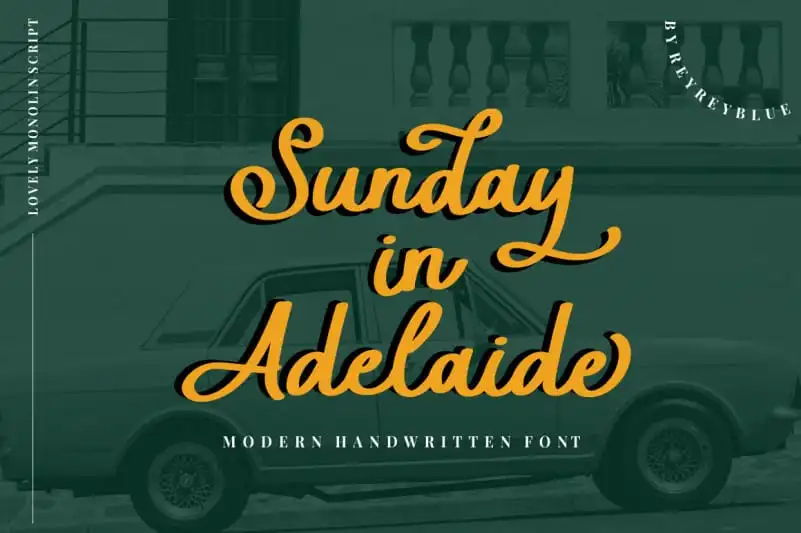
Sunday in Adelaide Script Font – Download Grátis
Descubra a encantadora “Sunday in Adelaide Script Font”, uma elegante e moderna tipografia feita para agregar profundamente às suas criações digitais. Ideal tanto para aplicações de logotipo, materiais de marcação quanto para estilos de evento, convites nupciais ou cartões festivos, esta fonte traz uma variedade de letras em maiúsculas e minúsculas, símbolos multilíngues, números, pontuação e ligaturas. Ademais, oferece suporte a swashes para um toque extra de personalização. “Sunday in Adelaide” é perfeita para aqueles que desejam incorporar uma textura única e delicada em seus projetos digitais, dando vida à identidade visual de seus trabalhos. Não espere mais para adquirir esta linda fonte – ela vai transformar a aparência de sua próxima criação digital.